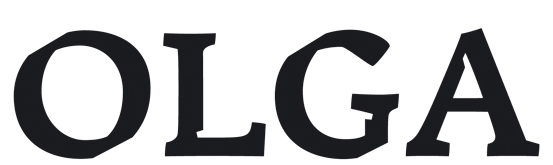
Ink Trap, Tintenfalle oder doch das Gegenteil
Interessante Diskussion heute bei Twitter. Ich rette sie mal auf eine Seite, wo man auch diskutieren und konservieren kann.
Heute von Erik van Blokland geschrieben:
Also auf gut Deutsch: Das öffnen einen Winkels ist keine Tintenfalle, sondern umgekehrt: die Tintenfalle ist der negative Effekt, den man durch das Öffnen des Winkel zu verhindern versucht.
Da könnte er von der Wortherkunft her sicher gut recht haben. Es macht so herum für mich auch mehr Sinn. Aber wie ich ja immer sage: Die Bedeutung eines Wortes ist dann richtig, wenn Sprecher/Schreiber und Hörer/Leser dasselbe meinen – nicht, weil es irgendwie historisch korrekt ist. Ein Hurenkind ist kein Kind einer Hure sondern der Satzfehler, den jetzt jeder Typoprofi vor sich sieht und genauso ist auch die Tintenfalle genau das, was wir darunter alle verstehen. Also von mir aus kein Handlungsbedarf. Aber ich wollte es trotzdem mal hier zur Diskussion stellen.
Darauf zielt es nicht ab. Gemeint ist: Wenn der Winkel zu spitz und unbearbeitet ist, wäre es eine Tintenfalle, denn da sammelt sich physisch oder optisch die »Tinte«.
Geht man jedoch dagegen vor und öffnet den Winkel, führt man eine Anti-Tintenfallenmaßnahme durch.
Im üblichen Sprachgebrauch benutzen wir es gerade umgekehrt.
Ist das denn so, dass man die immer öffnet? Ich dachte Inktraps wären verlängerte spitze Winkel, die, so zu sagen, kontrolliert zulaufen dürfen ...
"letting light in …" Aber genau das sollen sie doch gar nicht? Ich verstehe die Tintenfalle als ein konstruktives Mittel, um das Zulaufen den spitzen Winkels im Vorfeld auszugleichen, eben um im Endergebnis einen spitzen Winkel, nicht aber eine Aufhellung des Winkels, zu erhalten.
Lichtkeil beschreibt die Maßnahme gegen die Klecksbildung ziemlich treffend. Wie mit dem Hackebeil eine Kerbe schlagen, damit an dieser Stelle keine Tinte zusammenlaufen kann.
Das finde ich gerade nicht, weil "Licht" eben Helligkeit als Ergebnis assoziiert. Wenn das Ding sinngemäß "Tintenüberschussaufnahmekeil" hieße, wäre das in meinen Ohren treffend.
Zudem meine ich immer noch, dass die Tinte an der Stelle eben zusammenlaufen soll und nicht nicht kann, eben um als Ergebnis einen spitzen Winkel zu bekommen.
Gibt es denn einen anderen funktionalen Grund für eine derartige Ausgestaltung der Winkel?
Also, normal zur Sicherstellung: Sind die Dinger jetzt nur für den optischen Effekt oder zur ›kontrollierten‹ Aufnahme der Tinte, oder für beides so’n bisschen?
Physisch und optisch. Da wo ein spitzer Winkel in der Buchstabenform ist, kann physisch und/oder optisch ein Klecks entstehen. Also treibt der Schriftgestalter einen Lichtkeil in den Winkel, sodass weniger Druckfarbe an dieser Stelle aufgetragen wird und dann schlussendlich optisch ein vermeintlich normal aussehender, ungekleckster Winkel entsteht. Aber streng genommen wird ja eben an der Stelle, um die es geht, keine »Tinte in die Falle« gelockt, sondern sie wird im Gegenteil davon fern gehalten. Also eher eine »Tintenscheuche«. :-)
Es gibt natürlich auch Schriften, die das stilistisch nutzen.
Wo wir gerade beim Thema sind:
Gibt es denn auch einen Namen für das Gegenteil von Lichtkeilen?
Also ich meine diese Spitzen zum Beispiel bei der Copperplate Gothic.
Das sind ja keine Serifen, diese kommen meines Wissens daher, dass beim Gravieren die Ecken deutlich eckig und nicht rund erscheinen sollten. Ähnliches wurde wohl auch beim Fotosatz eingesetzt, da dort durch gewisse Unschärfen auch manche Ecken zu Rundungen tendierten.
Sind das dann Tintenkeile, Schwarzkeile oder sogar Schattenkeile? :-?
Ist das überhaupt noch interessant, da sie heute eigentlich gar keine technische Bewandtnis haben?
Ich habe es, wie offenbar Schnitzel und Bertel auch, immer so verstanden: Damit spitze Winkel nicht mit Tinte zulaufen, erweitert man die Winkel etwas, sodaß die Tinte nur in die Erweiterung läuft, wodurch dann die gewünschte Form entsteht. Diese Erweiterung, die zulaufen soll, bezeichnet man als Tintenfalle. Eigentlich ist der ursprüngliche, nicht erweiterte Winkel ja eine unerwünschte Tintenfalle, die Erweiterung eine erwünschte Tintenfalle.
An Erweiterungen, die nicht zulaufen, sondern zum optischen Ausgleich bestehen bleiben sollen, habe ich dabei nie gedacht. Ich finde, dafür sollte man einen anderen Ausdruck verwenden; „Lichtkeil“ oder allgemein „Lichtfalle“ finde ich passend.